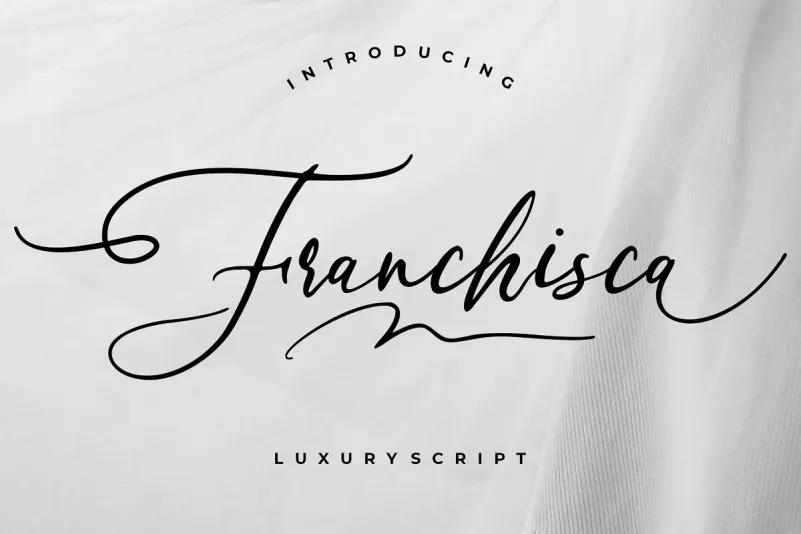
Franchisca Font é uma nova adição para quem busca uma tipografia script com toques de arte handmade. Inspirada no estilo do aquarela de escrevermos livros antigos, essa fonte apresenta caracteres decorativos e um fundo letra que dança sobre o texto. As linhas da base desse tipo de fonte se movem, criando uma sensação de vida e arte em cada palavra escrita. Perfeita para gráficos que buscam estilos artísticos sem perder a legibilidade do texto, Franchisca é um verdadeiro atalho direto para personalizar seus designs com uma qualidade única. Seja você um designer ou editor de imagens digitais, certamente encontrará em Franchisca Font uma maneira criativa e elegante de tornar seu trabalho ainda mais atraente.